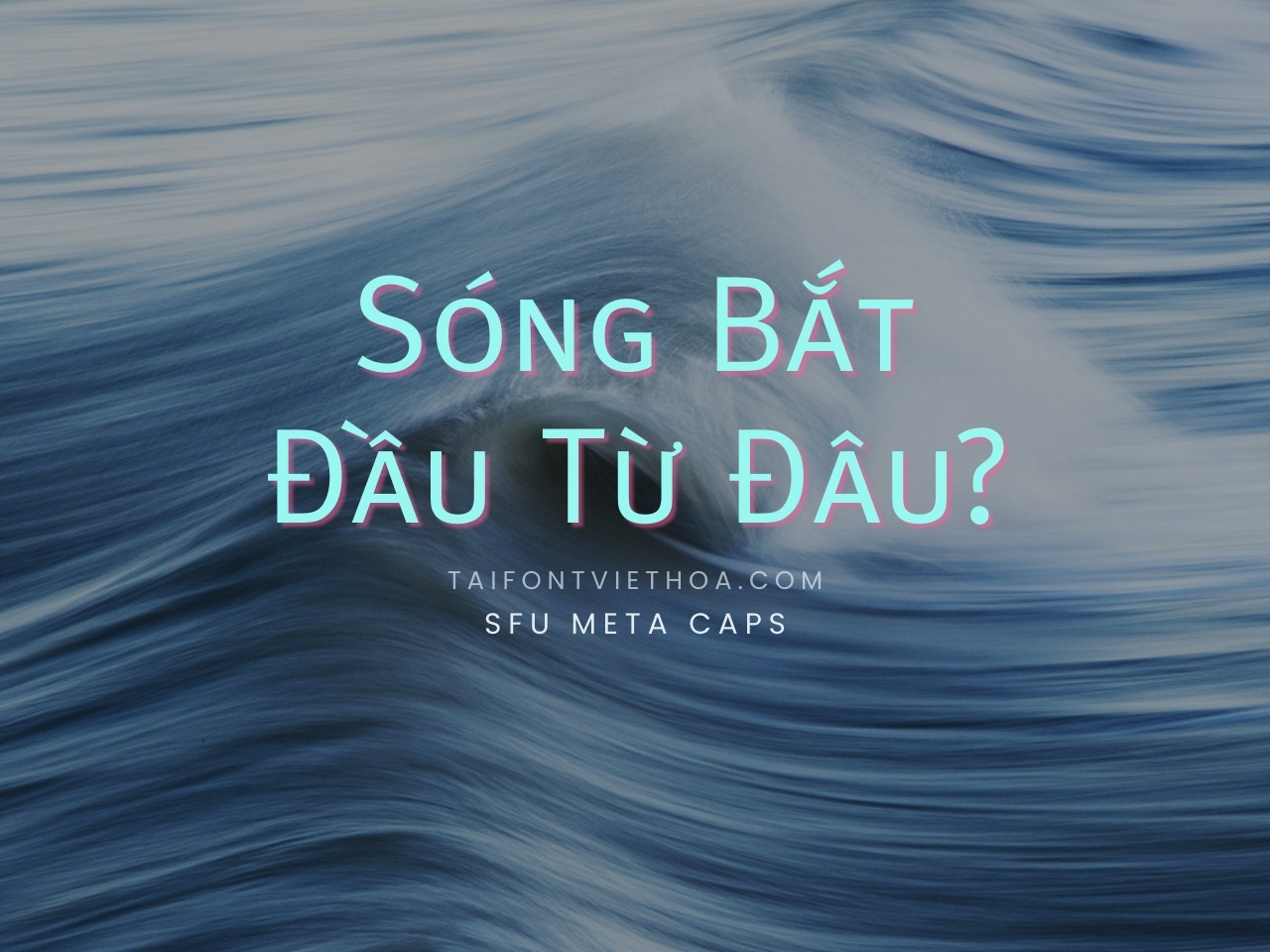
Font việt hóa SFU Meta
Giới thiệu về SFU Meta – Kiểu chữ hiện đại, rõ ràng và đa năng
SFU Meta là phiên bản Việt hóa của font Meta, một họ font sans‑serif hiện đại được thiết kế bởi Erik Spiekermann vào năm 1991 cho Deutsche Bundespost Đức. Thiết kế gốc nhấn mạnh sự rõ ràng, khả năng đọc và tính linh hoạt trong các thiết kế nhận diện thương hiệu, biển hiệu, poster và báo chí. Phiên bản Việt hóa — SFU Meta — được upload bởi Nguyễn Quỳnh Trâm Anh trên FontTiếngViet.com vào ngày 16/09/2023, tuy tác giả Việt hóa cụ thể chưa được xác minh rõ ràng.
Không chỉ hỗ trợ đầy đủ bảng ký tự tiếng Việt chuẩn Unicode, SFU Meta còn tương thích với hệ Latin Extended, phù hợp với nhiều ngôn ngữ châu Âu như tiếng Anh, tiếng Đức, tiếng Pháp… nhờ bộ glyph phong phú. Điều này giúp SFU Meta trở thành lựa chọn tối ưu cho thiết kế đa ngôn ngữ quốc tế.
Thiết kế & ứng dụng phong phú của SFU Meta
SFU Meta thuộc dòng sans‑serif hiển thị (display) với đặc trưng chiều cao x lớn, các nét chữ mở dễ đọc, và có đuôi chữ “l” giúp phân biệt rõ với “1” hoặc “I”. Font có độ tương phản trung bình đến thấp, giúp ứng dụng tốt ở nhiều kích thước từ tiêu đề lớn đến văn bản nhỏ.